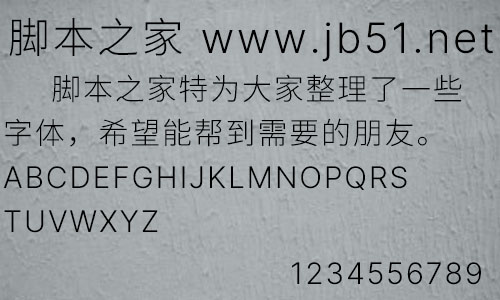
更紗黑體簡體 SC light 是一款不錯的可免費商用的藝術(shù)字體,字筆觸粗細(xì)適中,字形端正大氣,具有不錯的視覺感,適合應(yīng)用于藝術(shù)設(shè)計、平面宣傳設(shè)計、網(wǎng)頁設(shè)計,書法字帖等領(lǐng)域,需要的朋友可以前來本站下載。
更紗黑體(Sarasa Gothic),一款在100%縮放比例下有著優(yōu)秀渲染效果的字體,更紗黑體由Noto Sans / Iosevka和思源黑體的漢字部分合并而來,因此簡體中文基本不缺字,也有日系漢字的風(fēng)格,并且是開源免費字體。
更紗黑體與思源黑體對比,主要是英文部分顯示不同,英文顯示更時尚。而且增加了斜體。不過思源黑體具有7字重,而更紗黑體只有5字重,這一點比思源黑體差了一點。